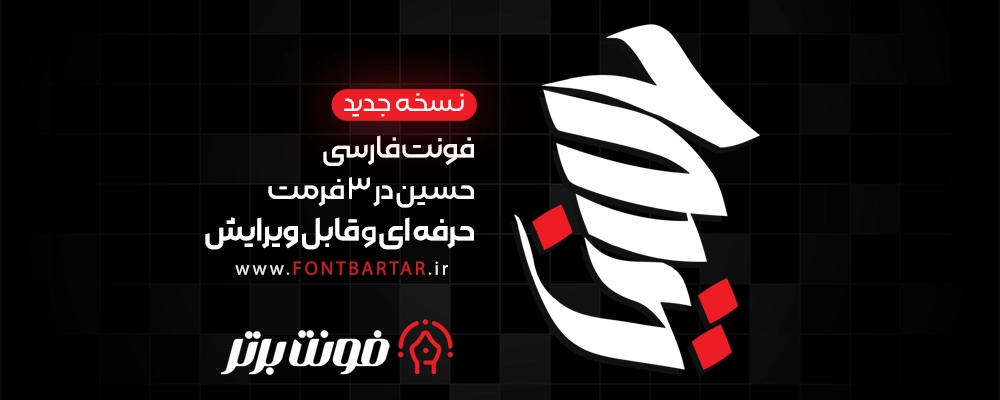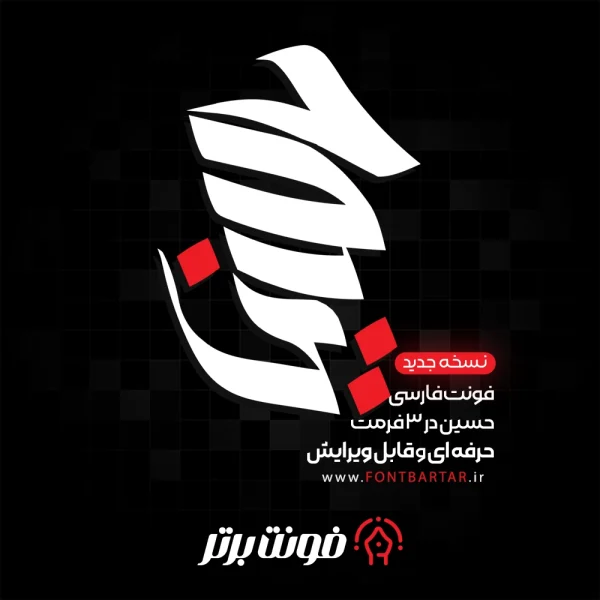
فونت فارسی حسین
با سلام خدمت کاربران همیشگی فونت برتر با عرض تسلیت به مناسبت آغاز ایام محرم در این مطلب از سایت با فونت فارسی حسین آشنا مبکنم. فونت تایپوگرافی و لوگوتایپ حسین یک فونت با طراحی حرفه ای و انعطاف پذیر می باشد ، شما با خرید فونت حسین می توانید بدون هیچگونه دانشی لوگو تایپ طراحی کرده و تایپوگرافی های زیبایی انجام دهید و از آن کسب درآمد کنید.
سریع و بدون دانش تایپوگرافی فقط و فقط با کنار هم قرار دادن حروف گرافیکی.